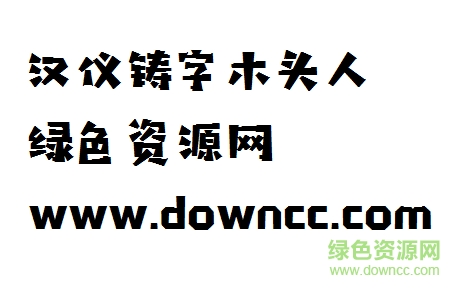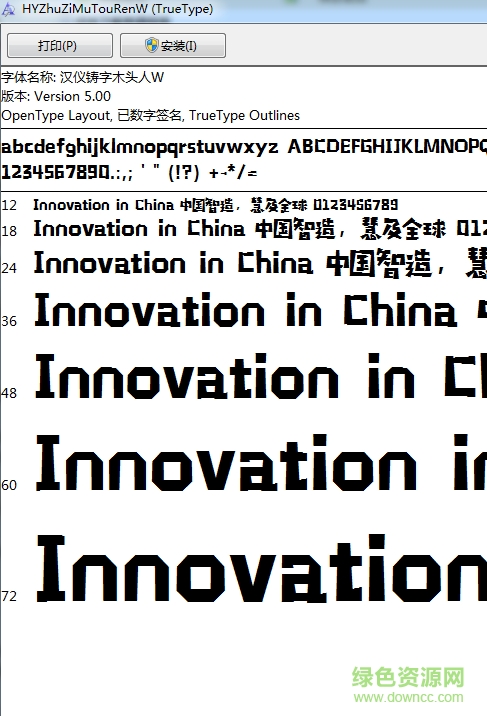
漢儀鑄字木頭人W字體是一款充滿童趣的中英文字體,字體整體效果非??蓯郏o人十分清新悠閑的感覺,好看至極,喜歡就到綠色資源網(wǎng)下載使用吧!
字體風(fēng)格:有力、穩(wěn)重、堅(jiān)硬、休閑、有趣、可愛、快樂;
推薦場景:標(biāo)志、廣告、游戲動漫、影視、圣誕節(jié)、萬圣節(jié)、兒童節(jié);
漢儀鑄字木頭人字體趣味性極強(qiáng),用來裝酷賣萌再合適不過了,萌萌的木頭人形狀非常好玩,歡迎廣大網(wǎng)友前來下載使用!